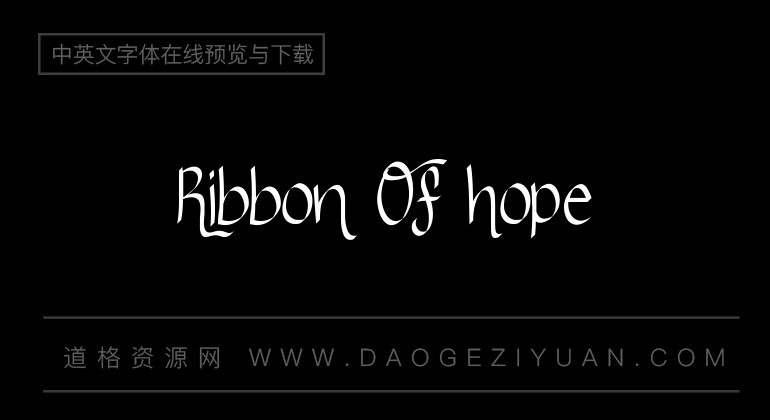
Ribbon Of hope
吧? Ribbon of Hope字体是一款简洁、优雅、美观的字体,它由一系列细长的线条构成,给人以希望、温暖、慰藉的感觉。它的字母形状细腻优美,适合用于慈善活动、慰问信函、慰问卡片等特殊场合的文字排版。
Ribbon Of hope是一款非常不错的手写艺术字体,具有很好的视觉感,适合于文化类的宣传设计、商业类品牌的广告和产品包装设计以及个性化文字排版等较多场景。